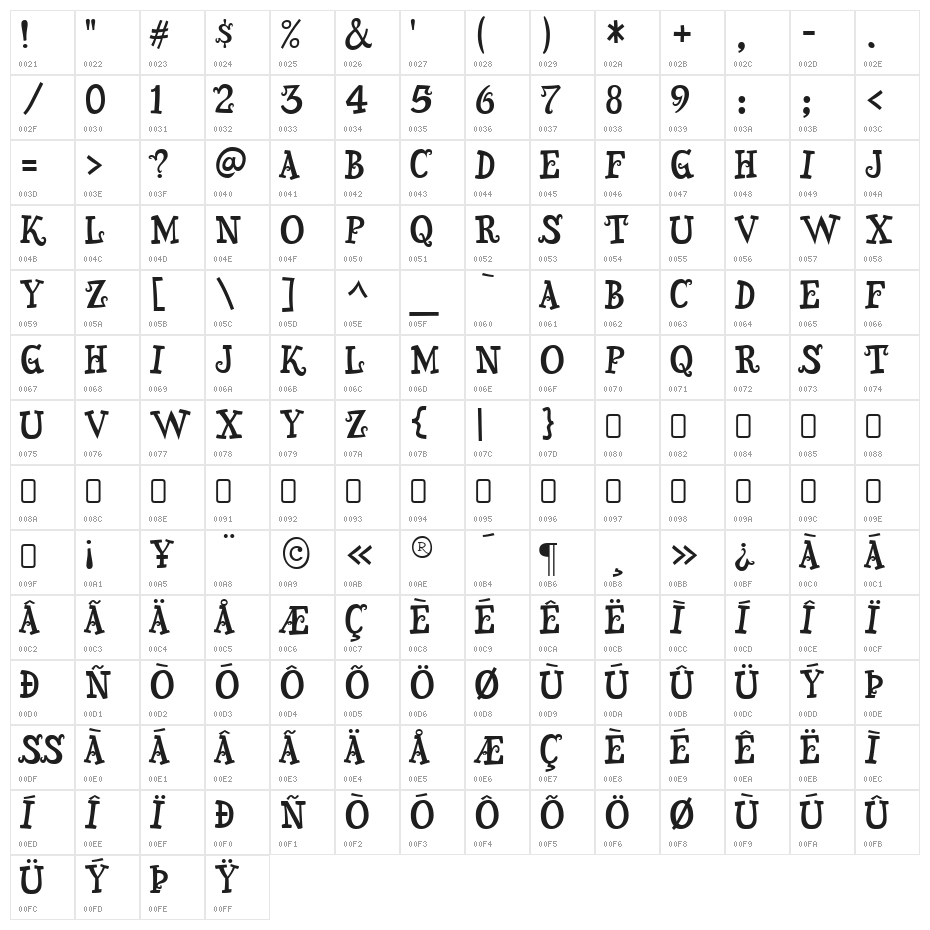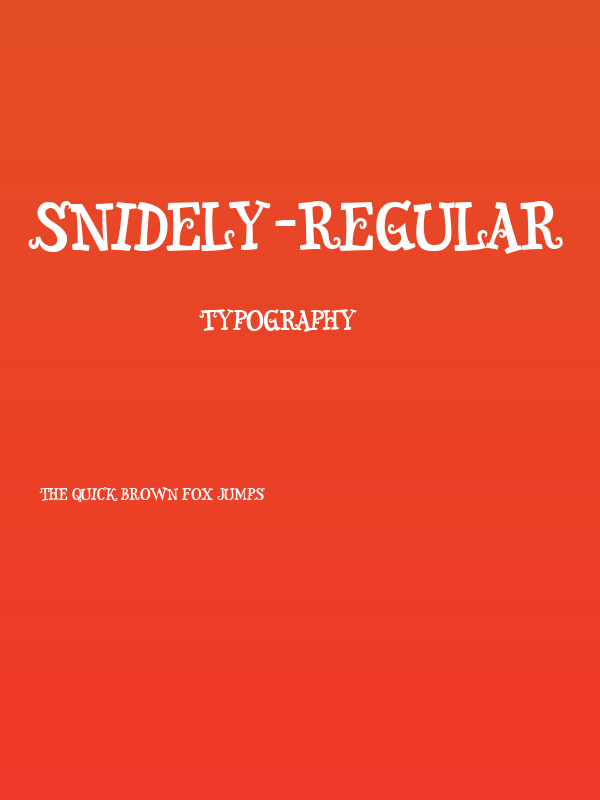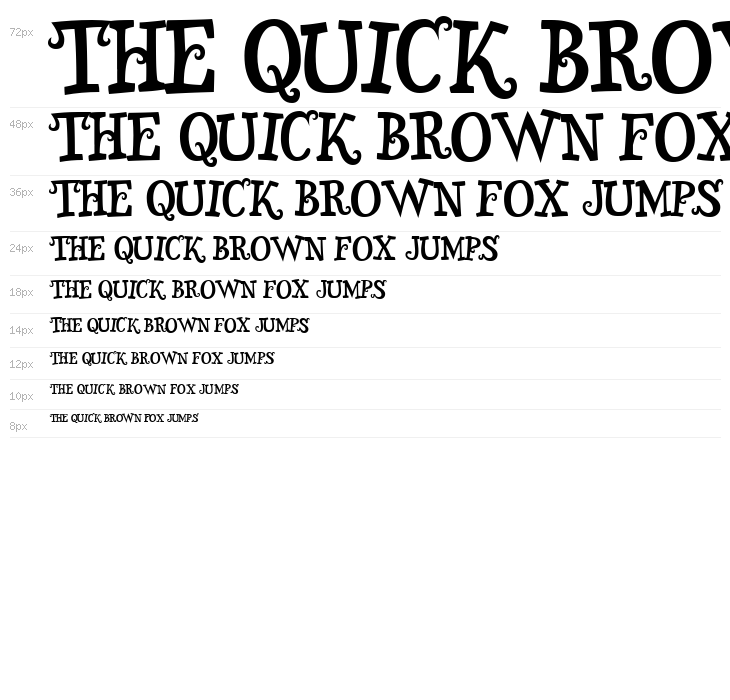
Snidely-Regular Font
| 全体的なスタイル | Playful and Whimsical |
| おすすめプロジェクト | Ideal for children's books, playful branding, festive invitations, and creative posters. |